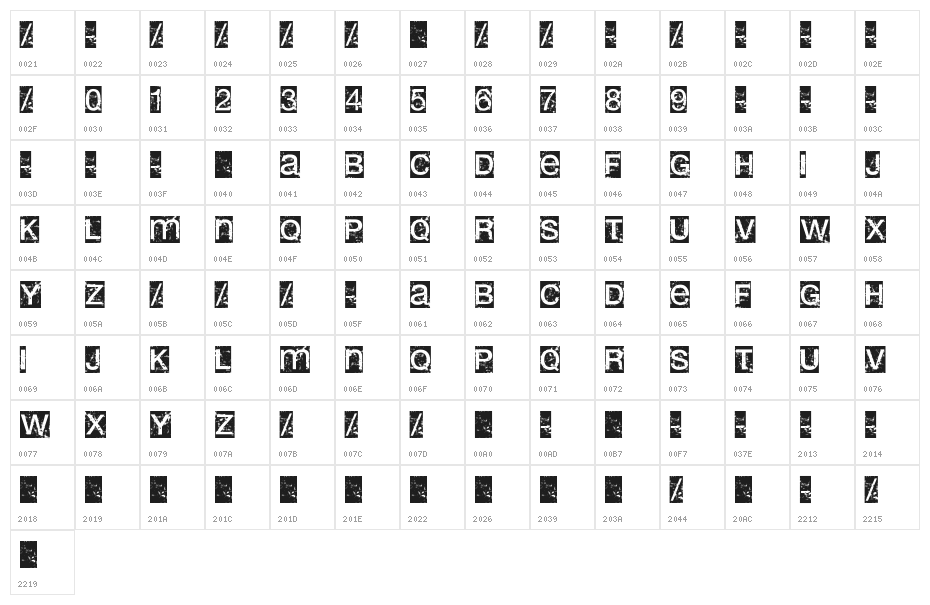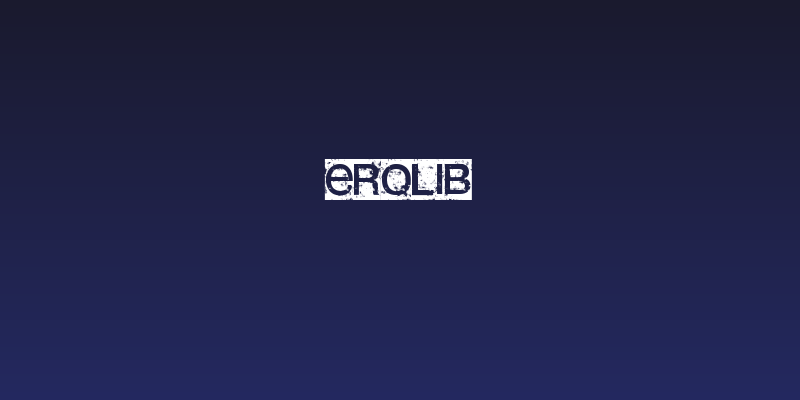
erolib Font
✎ Distorted Eroded
| Kategorien | Distorted Eroded |
| Gesamtstil | Vintage |
| Vorgeschlagene Projekte | Ideal for album covers, posters, branding for edgy or vintage-themed products, and any design requiring a bold, textured look. |